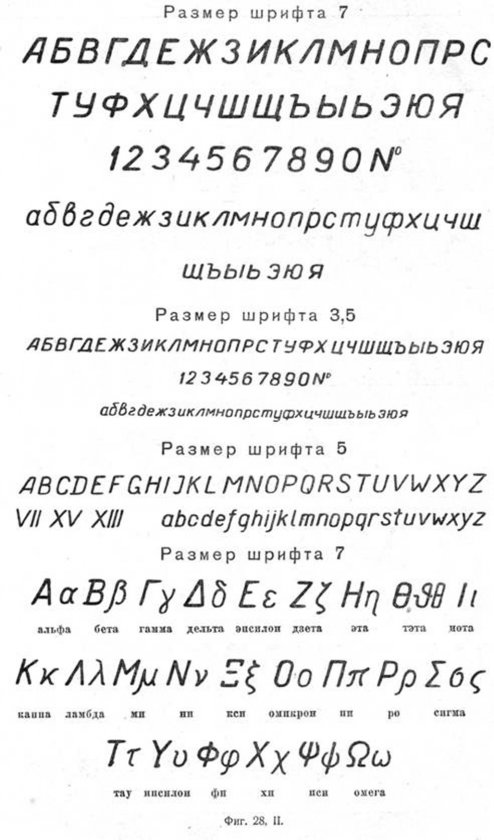
Размеры букв и цифр чертежного шрифта
Буквы черчении
Все надписи на чертежах должны быть выполнены чертежным шрифтом (рис. 24).
Начертание букв и цифр шрифта устанавливается стандартом. Стандарт определяет высоту и ширину букв и цифр, толщину их линий обводки, расстояние между буквами, словами и строками. Чтобы научиться надписывать чертежи стандартным шрифтом, надо знать не только характер начертания букв и цифр, но также и их размеры.
Стандарт устанавливает следующую высоту (она обозначается h, читается «аш») прописных (заглавных) букв и цифр: 2,5; 3,5; 5; 7; 10 и 14 мм. Высота прописных букв (рис. 25) в миллиметрах соответствует размеру шрифта.
Ширина большинства прописных букв равна 4/7 высоты.
Исключение составляют буквы Ж, Ф, Ш, Щ, Ы, Ю, ширина которых равна 6/7 h, и букв А и М, ширина которых равна 5/7 h, т. е. немного меньше высоты. Нижние и боковые отростки букв Д, Ц, Щ, Ъ, цифры 4 и верхний элемент буквы Й выполняются зa счет промежутков между строками и буквами
Эти соотношения установлены для основного чертежного шрифта.
Однако стандарт разрешает использовать и широкий шрифт. Ширина букв такого шрифта больше тех же букв основного шрифта на 1/7 h.
Буквы и цифры чертежного шрифта имеют наклон к линии строки примерно 75° (рис. 25). Некоторые надписи допускается выполнять без наклона.
Высота строчных букв равна 5/7 высоты прописных букв
(рис. 25), что примерно соответствует высоте следующего меньшего размера шрифта. Например, высота строчных букв для шрифта 10 будет равна 7 мм. Исключение составляют буквы б, в, д, р, у и ф. Их общая высота равна Л.
Ширина строчных букв равна 3/7 h, кроме букв ж, т, ф, ш, щ, ы, ю, ширина которых равна примерно их высоте, и буквы м, имеющей ширину 4/7 h.
Цифры имеют те же размеры, что и прописные буквы, кроме цифры 1; ее ширина 2/7 h. Расстояние между буквами и цифрами в словах принимают равным 2/7 h, между словами и числами не менее ширины букв текста. Расстояние между нижними линейками строк должны быть равны не менее 1.5 h.
Высота букв и цифр на чертежах, выполненных в карандаше, должна быть на менее 3,5 мм.
Толщину линий букв и цифр выбирают равной примерно 1/7 h
В черчении и геометрии вам придется пользоваться буквами латинского шрифта. Их начертание показано на рис. 26.
Как писать чертежным шрифтом.
Оформлять чертежи надписями надо аккуратно. Нечетко сделанные надписи или небрежно нанесенные цифры в размерах могут быть неправильно поняты при чтении чертежа. На заводе в таких случаях неизбежен брак в работе.
Чтобы научиться красиво писать чертежным шрифтом, вначале для каждой буквы чертят сетку (рис. 27). Позже можно проводить только верхнюю и нижнюю линии строки.
Контуры букв намечают тонкими линиями. Убедившись, что они написаны правильно, их обводят мягким карандашом.
Для быстроты выполнения надписей чертежным шрифтом иногда пользуются различными трафаретами и шаблонами (их можно купить в магазине). При этом прописные и строчные буквы в одном слове могут иметь одинаковую ширину.
При кажущемся увеличении промежутков между некоторыми прописными буквами (например, в слове «станок» между Т и А) эти промежутки уменьшают до размера, равного толщине линий букв (см.
рис. 27).
А теперь посмотрим, какой шрифт следует выбирать для заполнения основной надписи. Надписи «Чертил», «Проверил», номер школы и класс рекомендуется выполнять шрифтом 5. Наименование чертежа или детали пишут шрифтом 7, а название материала — 3,5 или 5. Масштаб и номер чертежа тоже можно писать шрифтом 5
Расстояние между нижними линейками строк должны быть равны не менее 1.
Чертежный шрифт
Шрифт (от нем. Schrift) — это рисунок, начертание букв ка кого-либо алфавита, цифр и знаков.
Шрифты чертежные (ГОСТ 2.
304-81) предназначены для выполнения надписей, начертания условных знаков и размерных чисел на чертежах. Для выполнения надписей в черчении используют ГОСТ. ГОСТ устанавливает номера чертежных шрифтов (1,8; 2,5; 3,5; 5; 7; 10; 14; 20; 28; 40) русского, латинского и других алфавитов.
Первый стандарт «Шрифты для надписей» был разработан и утвержден в 1919 г.
Номер шрифта соответствует высоте (h) прописной буквы. Например, шрифт № 5 имеет высоту прописной буквы, равную 5 мм.
Высота буквы измеряется перпендикулярно к основанию строки. Шрифт выполняется с наклоном в 75° (ГОСТом допускается выполнять надписи чертежным шрифтом без наклона).
Для удобства написания букв чертежного шрифта выстраивают вспомогательную сетку (рис. 35), которую выполняют следующим образом. Проводят нижнюю и верхнюю линии строки, расстояние между которыми равно высоте прописной буквы. Откладывают на нижней линии строки ширину букв и расстояние между ними (табл. 3).